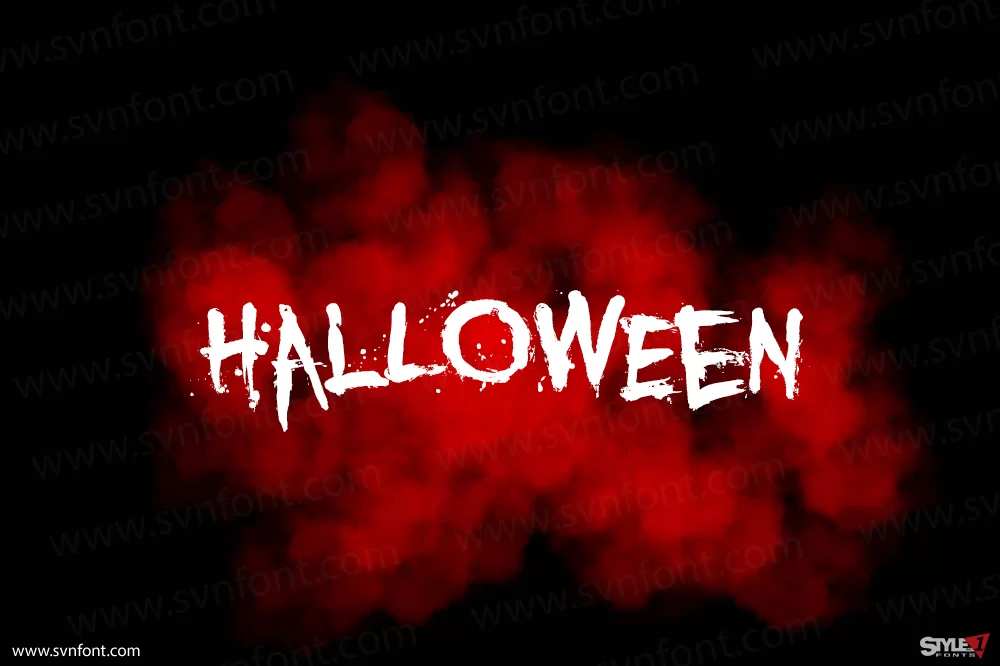
You Murder BB là một font chữ viết tay phong cách kinh dị, phù hợp cho các dự án về phim ảnh và logo cần yếu tố đáng sợ, kịch tính và bí ẩn. Font chữ này mang đến cảm giác thủ công, như thể được viết bằng tay bởi một nhân vật phản diện, với các đường nét thô ráp, không đều và đầy tính ngẫu nhiên. Những đường nét sắc nhọn, các ký tự biến dạng tạo nên một không khí đe dọa và hồi hộp, phù hợp cho các dự án phim kinh dị, logo các thương hiệu liên quan đến thể loại kinh dị hoặc những sản phẩm cần tạo cảm giác kỳ bí, rùng rợn.
"You Murder BB" giúp nâng tầm yếu tố thị giác, thu hút người xem ngay lập tức, đồng thời truyền tải thông điệp một cách mạnh mẽ và ấn tượng.